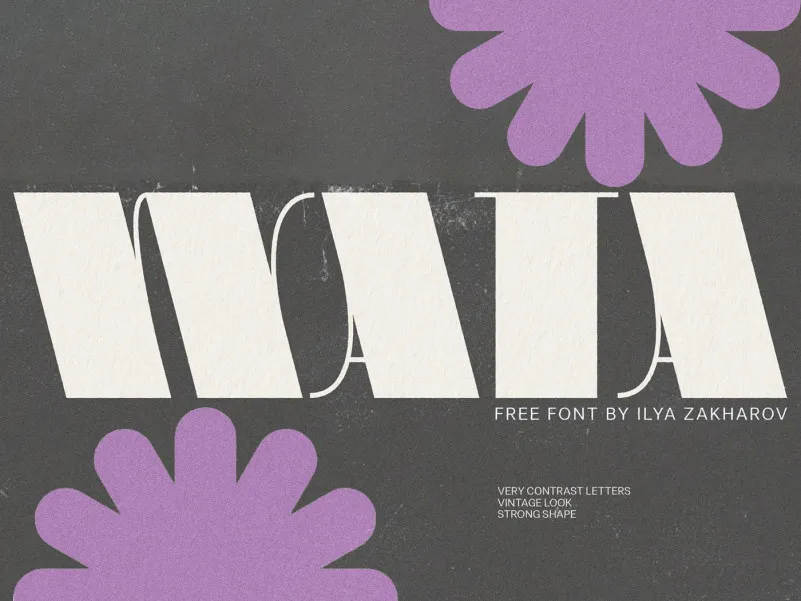
WATA Font – Download Grátis
A WATA Font é uma tipografia de display criada para ser usada em grandes tamanhos, especialmente nas aberturas de revistas, capas e quaisquer outras situações onde se deseja destacar a elegância com um impacto audível. Com linhas retas e robustas, essa fonte foi pensada para impressionar ao usar em áreas públicas como lojas ou estabelecimentos comerciais, iluminando o design do seu material de forma atraente. Perfeita para criar uma impressão forte e memorável, a WATA Font oferece um tom firme que se adequa perfeitamente à natureza destes espaços onde deseja chamar atenção. Além disso, com seus traços finos e curtos em alguns pontos, essa fonte traz um toque extra de sofisticação sem deixar de ser profissional. Seja ela usada para título ou corpo do texto, a WATA Font oferece uma opção perfeita para quem deseja dar seu design o impacto desejado ao se destacar em qualquer situação.